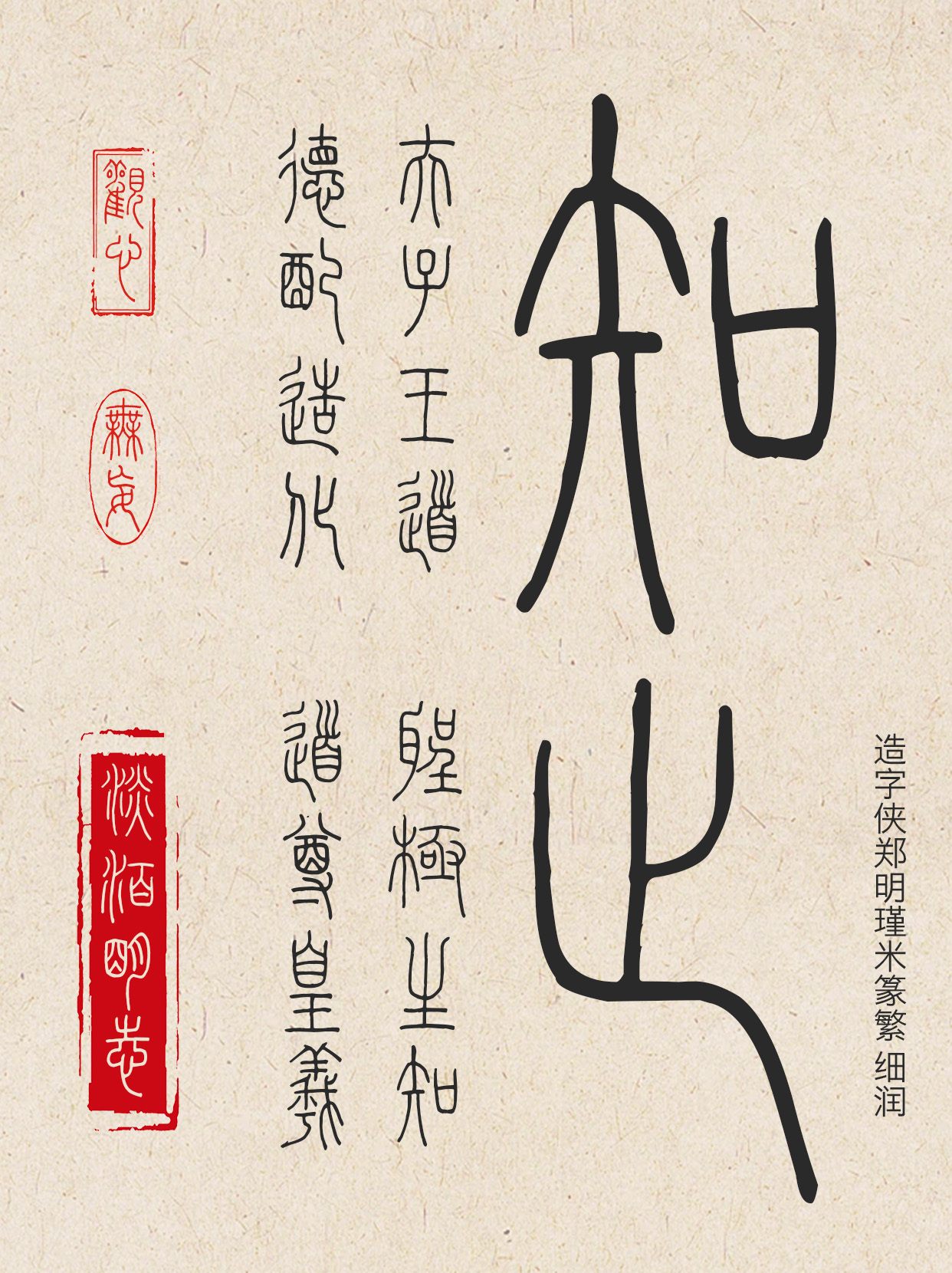
造字侠郑明瑾米篆繁 细润
PlayFont-MizhuanT-Light
案頭丹篆小符靈
造字侠郑明瑾米篆繁 细润是一款硬笔小篆字体,结构遵循对称均衡的小篆构字法则。笔画线条粗细匀称,起收用笔圆润,转折圆柔,既保留了篆书“玉箸篆”的线条质感,又适配硬笔书写的利落特性。适合应用于海报设计、艺术展览、书籍装帧等多种领域。